Как проверить, что правка буквы не испортила другие знаки
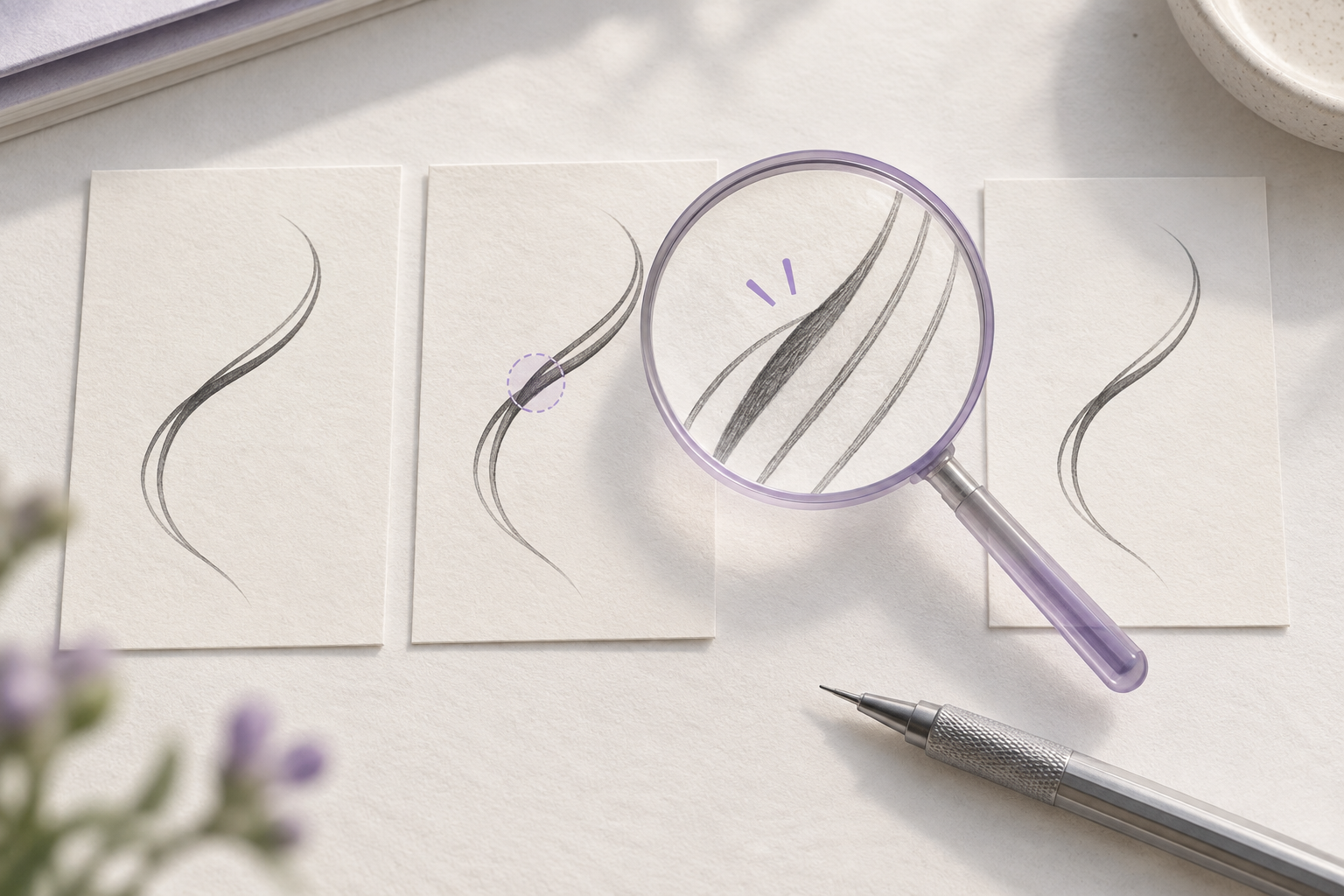
После первой сборки шрифта исправление одной буквы может незаметно ухудшить соседние: изменённый наклон меняет ритм слова, новый штрих начинает сливаться с другим знаком, а общий фильтр обработки затрагивает весь набор. Чтобы поймать такие побочные эффекты, сохраняйте исходный экспорт, заранее выбирайте контрольные слова и сравнивайте одну правку в нескольких контекстах. Ниже — рабочая процедура регрессионной проверки без сложной системы тестирования.
Что считать побочным эффектом
Побочный эффект — заметное ухудшение, появившееся вместе с правкой, хотя его не было в исходной версии и оно не входило в задачу. Вы изменили форму «к», чтобы сделать её яснее, а в словах с «к» теперь возник чрезмерный просвет; скорректировали толщину штриха, и тонкие детали в нескольких других буквах стали тяжелее. Это не означает, что любое изменение соседнего знака является ошибкой. Нужно понять, связано ли оно с решением, мешает ли реальному использованию и можно ли его подтвердить повторной проверкой.
Полезно различать три ситуации. Первая — целевое улучшение: исходная проблема стала меньше. Вторая — допустимый компромисс: одна деталь немного изменилась, но это не влияет на читаемость и общий характер. Третья — регрессия: стало труднее распознавать знак, читать слово, сохранять единый ритм или использовать гарнитуру в выбранном формате. Если смешать эти оценки в одно «нравится / не нравится», решение будет зависеть от последнего впечатления.
До изменения зафиксируйте точку сравнения
Сохраните рабочий файл и экспорт, который предшествует правке. Дайте им однозначные имена, например test-v03-before-k.ttf и test-v03-before-k.otf, и не перезаписывайте контрольную копию. Если проект ведётся в редакторе с историей, убедитесь, что старое состояние действительно открывается и экспортируется. Скриншот не заменяет файл: он полезен для визуального сравнения, но не позволяет перепроверить гарнитуру в новом приложении или размере.
Запишите, что именно собираетесь изменить, и сформулируйте наблюдаемую цель. Вместо «подтянуть букву» напишите: «в слове “какао” строчная “к” кажется слишком широкой; проверить более узкий правый просвет». Отдельно укажите, где заметили проблему, какой результат ожидаете и что не должно ухудшиться. Такой короткий критерий предотвращает расширение задачи: во время правки автор видит новые мелочи и начинает менять всё подряд.
До экспорта подготовьте две-три контрольные строки. Включите исходное проблемное слово, несколько слов с тем же знаком в разных окружениях и обычное предложение. Если меняете «к», пригодятся, например, «краска», «окно», «рука» и «книга»: положение в начале, середине, конце и рядом с разными соседями меняет впечатление. Не ищите один универсальный тестовый текст: подбирайте слова к конкретной причине правки.
Составьте карту возможного влияния
У правки есть непосредственная область и зона риска. Непосредственная область — знак или параметры, которые вы меняете. Зона риска — то, что может измениться вместе с ними: похожая буква, соседний глиф в слове, интервал, связка штрихов, размерное поведение или общий характер набора. Перед работой перечислите два-три наиболее вероятных последствия, а не весь алфавит.
Например, изменение наклона у «л» может повлиять на различимость с «м» в тесных сочетаниях. Утолщение пера может сделать тяжелее не только целевую букву, но и все знаки, созданные тем же способом. Уточнение формы заглавной буквы может нарушить баланс прописных, даже если отдельная форма стала изящнее. Если вы не знаете, какие знаки связаны общей операцией, проверьте область действия инструмента или этапа экспорта, прежде чем считать правку локальной.
Составьте маленькую таблицу или заметку: что меняется, что проверить, на каком примере. Например: «наклон “л” — пары “л/м” — слова “лом”, “мыло” и короткая строка»; «толщина пера — тонкие и широкие элементы — набор “и ш ж” и обычный абзац». Эта карта не обязана быть исчерпывающей. Её назначение — сделать сравнение осмысленным и не забыть очевидный риск.
Если правка затрагивает общий процесс
Иногда причина не в одном глифе, а в операции, которая применяется ко всему набору: например, меняется способ очистки изображений, масштабирование или общая настройка экспорта. Тогда точечная проверка исходного слова не покажет полный охват. Составьте короткий список типичных представителей: округлый знак, тонкий элемент, знак с выносной частью, плотная группа штрихов и несколько цифр. Сравните их в одинаковых пробах и отдельно отметьте, какие классы изменились.
Не нужно проверять каждый знак при любой смене параметра. Выберите примеры, которые способны показать разные последствия одной операции. Если изменение затрагивает все глифы, добавьте строку с полным набором символов, но не принимайте её за проверку чтения: сплошной ряд показывает неравномерность, а слова выявляют взаимодействие соседних форм. Когда общий процесс стал причиной дефекта, откатите настройку и повторите экспорт на копии проекта, прежде чем редактировать отдельные буквы вручную. Иначе локальные компенсации могут скрыть источник проблемы и усложнить следующий проход.